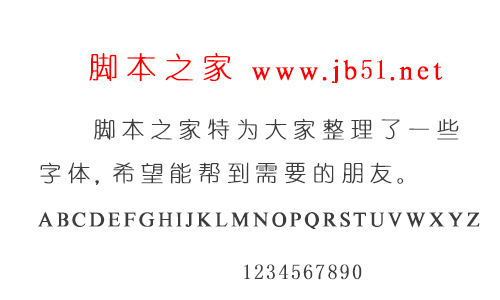
蘭米黑圓體是蘭米字庫(kù)推出的一款標(biāo)準(zhǔn)藝術(shù)字體,字體工整簡(jiǎn)潔,具有強(qiáng)烈的視覺(jué)沖擊力,適應(yīng)于報(bào)紙和雜志和書(shū)籍中常用字體, 海報(bào)、個(gè)性促進(jìn)品牌標(biāo)志設(shè)計(jì)、字體設(shè)計(jì)、等環(huán)境使用,歡迎喜歡蘭米黑圓體的朋友前來(lái)下載使用。